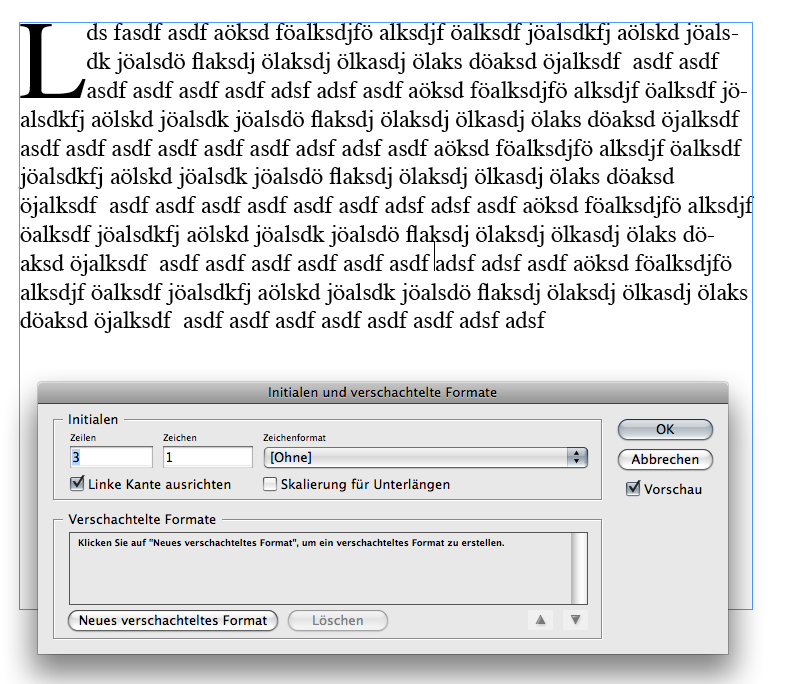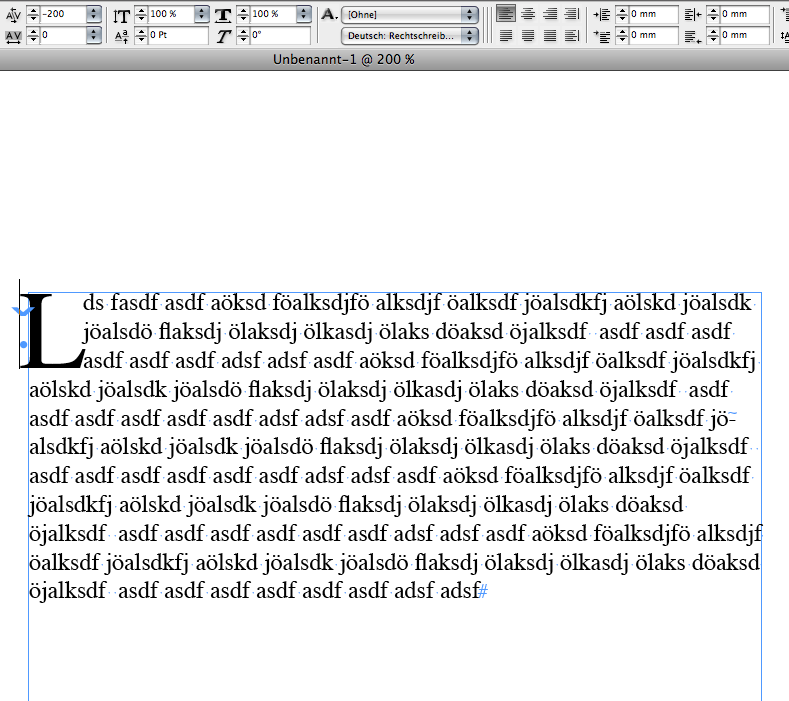
Initialen - Konsequenz bei Verwendung?
wenn ich Initialen samt vorangegangener Leerzeile verwende, muss ich dann so konsequent sein und bei jedem neuen Absatz mit vorangegangener Leerzeile Initialen verwenden?
Oder kann ich sie verwenden, wie ich es gestalterisch für sinnvoll halte?
ich denke die var. 1 wird dann schnell überladen.
eher var. 2, wobei es natürlich schon fein wäre, wenn der einsatz der initialen auch einer inhaltlichen logik folgen würde, zb abschnittsgliederung etc.
Ich habe immer recht kurze Texte im Magazin, wonach das "überladen" wohl nicht zutrifft. Mist, ist halt wieder so ein Sonderfall bei mir ...
Initialen sind eine Art der Auszeichnung, und sollten meiner Meinung nach daher wie alle Auszeichnungen irgendeiner inhaltlichen Logik folgen. Du setzt ja auch nicht einfach irgendwelche Wörter kursiv, weil's hübsch aussieht! Wenn ein Absatz mal mit einem Initial beginnt, ein anderer aber nicht, wird der Leser verwirrt.
ich halte mal dagegen: initialen sind eine art der dekoration – und ornamente müssen nicht einer bestimmten logik folgen. sie können mal hier, mal da vorkommen, wie es eben gerade schön aussieht, ohne dass symmetrie oder irgendeine andere form von regelmäßigkeit zwingend wäre. eine verzierende st-ligatur setze ich in einer überschrift auch nicht an jeder stelle, an der diese buchstabenkombination vorkommt, sondern nach gefühl.
In meinem Fall war es so, dass ein fach-fremder Leser verwirrt war: Werde nun wohl noch einmal drüber gehen müssen.
Noch problematischer finde ich derzeit, dass ich nun so ohne weiteres wohl keinen Überhang zum Randausgleich mehr hin bekomme:
In xPress 8 sollte das manuell gehen, in Indesign vorläufig nur über den Trick, vor dem Initial ein weiteres, unsichtbares Zeichen (z.B. Hairspace) einzufügen, und den darauffolgenden Buchstaben dann manuell "zurück" zu unterschneiden – dann geht's auch "aus dem Rahmen raus".
Das ist natürlich weder elegant noch automatisiert.
Dann geht mir aber a. Das Initial flöten (was man noch irgendwie hinbekommen könnte) und b. komme ich so (Alt+Pfeil) auch nicht über den Textrahmen hinaus.
Screenshots aus Indesign CS3.
Hier die Option "Linke Kante ausgleichen", damit schlägt Indesign offenbar den Initial an den Rahmenrand an.
Wenn du hier die Option "Zeichen" auf 2 stellst, und dann vor den eigentlichen Initial ein Leerzeichen stellst, bleibt er erhalten, und folgendes wird (bei mir zumindest) möglich:
(Unterschneidung auf -200 zwischen Leerzeichen und L)
Ich kann hier auch aus dem Rahmen hinauswandern, das geht bei dir nicht?